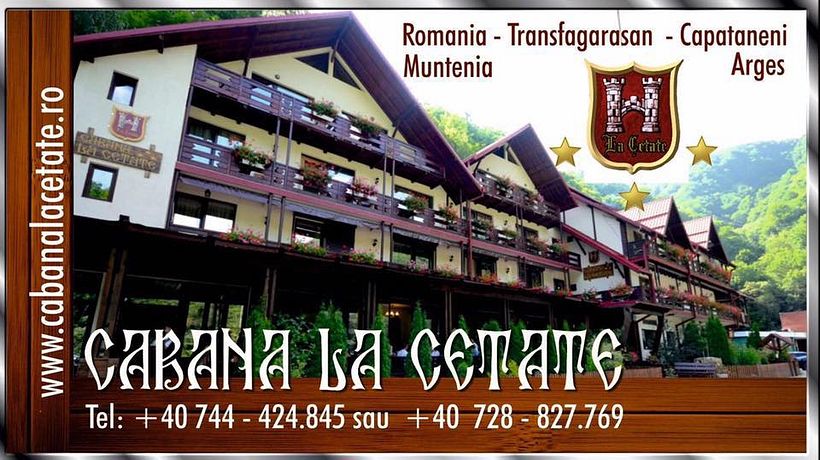
Dudas sobre tipografías
Buenas! Estoy buscando a alguien capaz de identificarme un par de tipografías o proporcionarme el nombre de otras similares. El motivo es simple: voy a tatuarme con dichas fuentes, si las encuentro!
La primera sería algo muy parecido a la de la frase: CABANA LA CETATE. Es muy común en Transilvania, donde viví un tiempo, pero no consigo encontrarla entre otras fuentes medievales.
Shelley Andante
Ya que estamos, me gustaría consultar sobre un par más.
Las tipografías del cartel principal de la pastelaría y la de los cartelitos más pequeños (que según veo son diferentes).
Esta misma o alguna muy parecida, puesto que no la encuentro al completo para descargar.
La segunda es claramente la Troy Type de Morris.
La primera la he tenido que buscar, parece una blackletter pero particular y como dices propia de Rumanía o por ahí, aunque yo juraría haberla visto por aquí también en algún pub de ambiente pretendidamente medieval, celta y tal.
Aquí hay una similar gratuita.